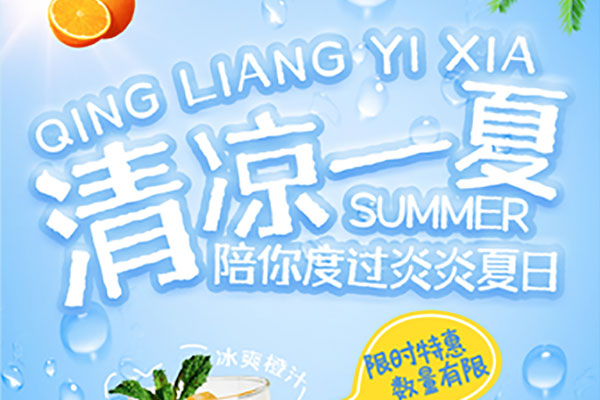
千图雪花体
千图雪花体:复古与力量感的完美结合
千图雪花体是一款由千图网精心打造,集复古与力量感于一体的黑体标题字。这款字体以黑字字形为基础,独具匠心地加入了雪花元素,不仅营造出一种怀旧的复古感,同时还呈现出力量充沛的视觉效果。
千图雪花体的每一个字形都经过精心设计,呈现出粗壮且有力的笔画,强化了整体的力量感。同时,这款字体的字面较大,使得文字在排版时更加醒目,更能吸引人们的目光。无论是在视觉还是心理上,都能给人们带来强烈的冲击力。
这款字体非常适合用于各类复古风格的品宣广告和页面设计上,无论是复古主题的海报、宣传册,还是网页上的复古风格页面设计,千图雪花体都能够完美地呈现出复古与力量感的魅力。
千图雪花体效果预览
千图雪花体字体效果预览